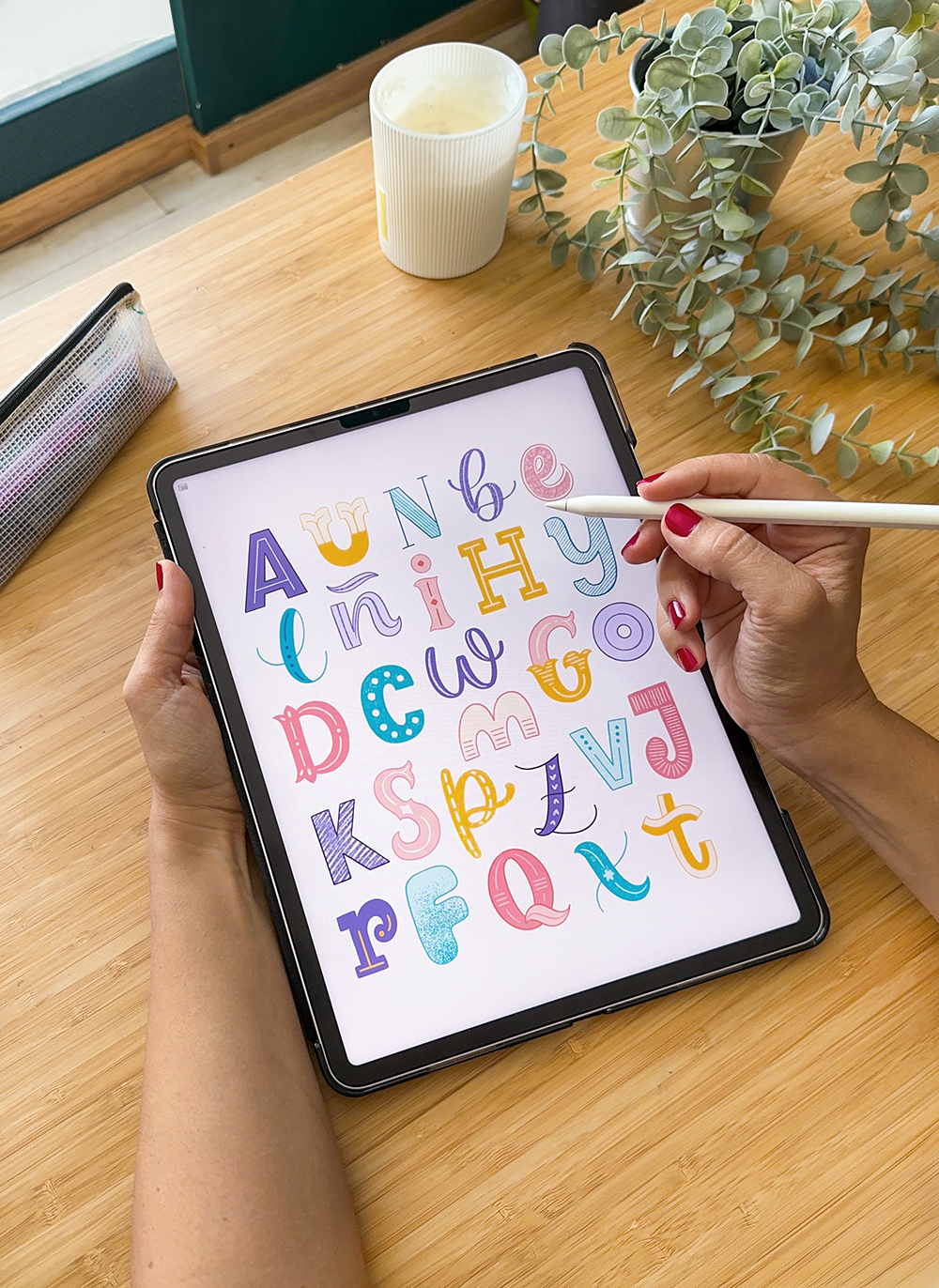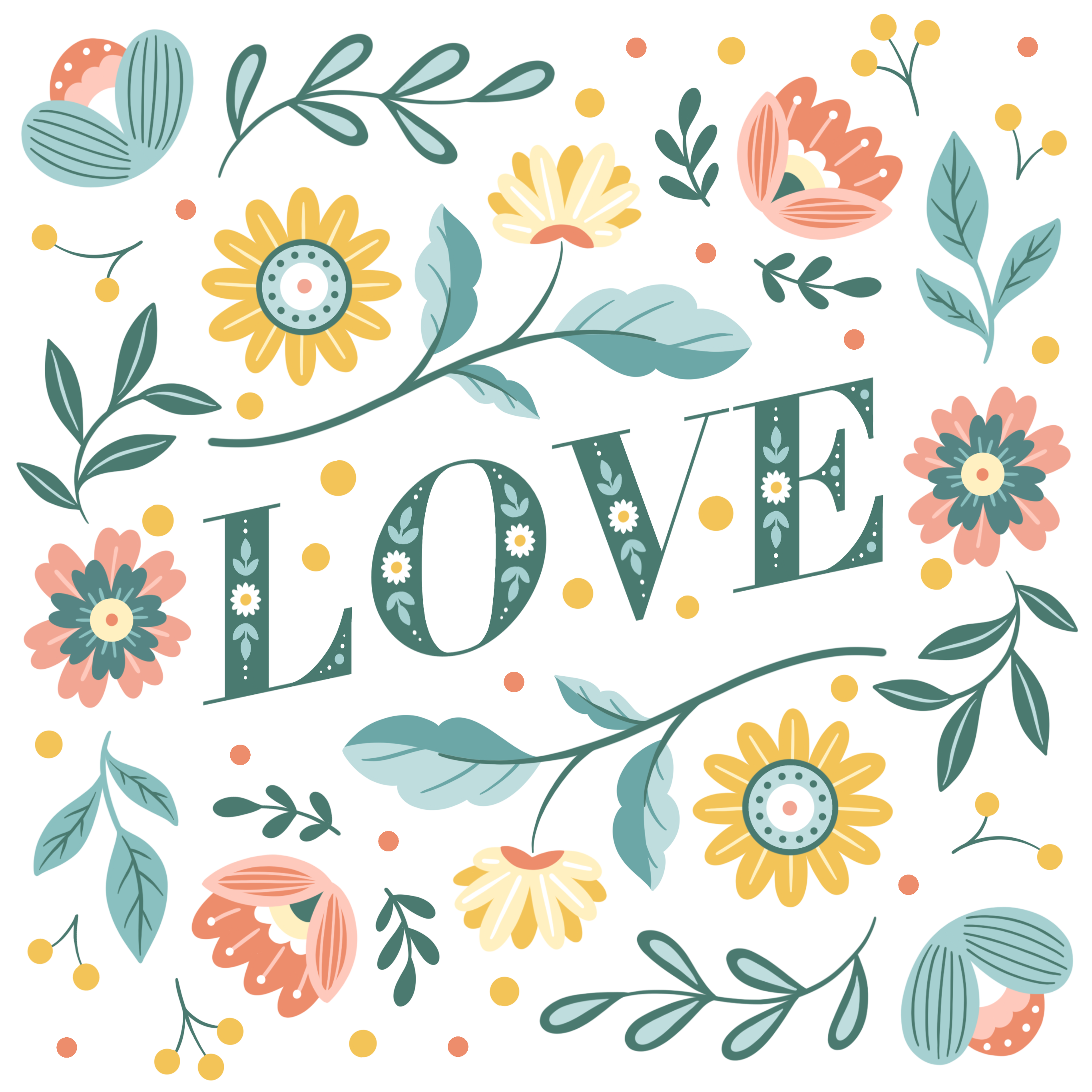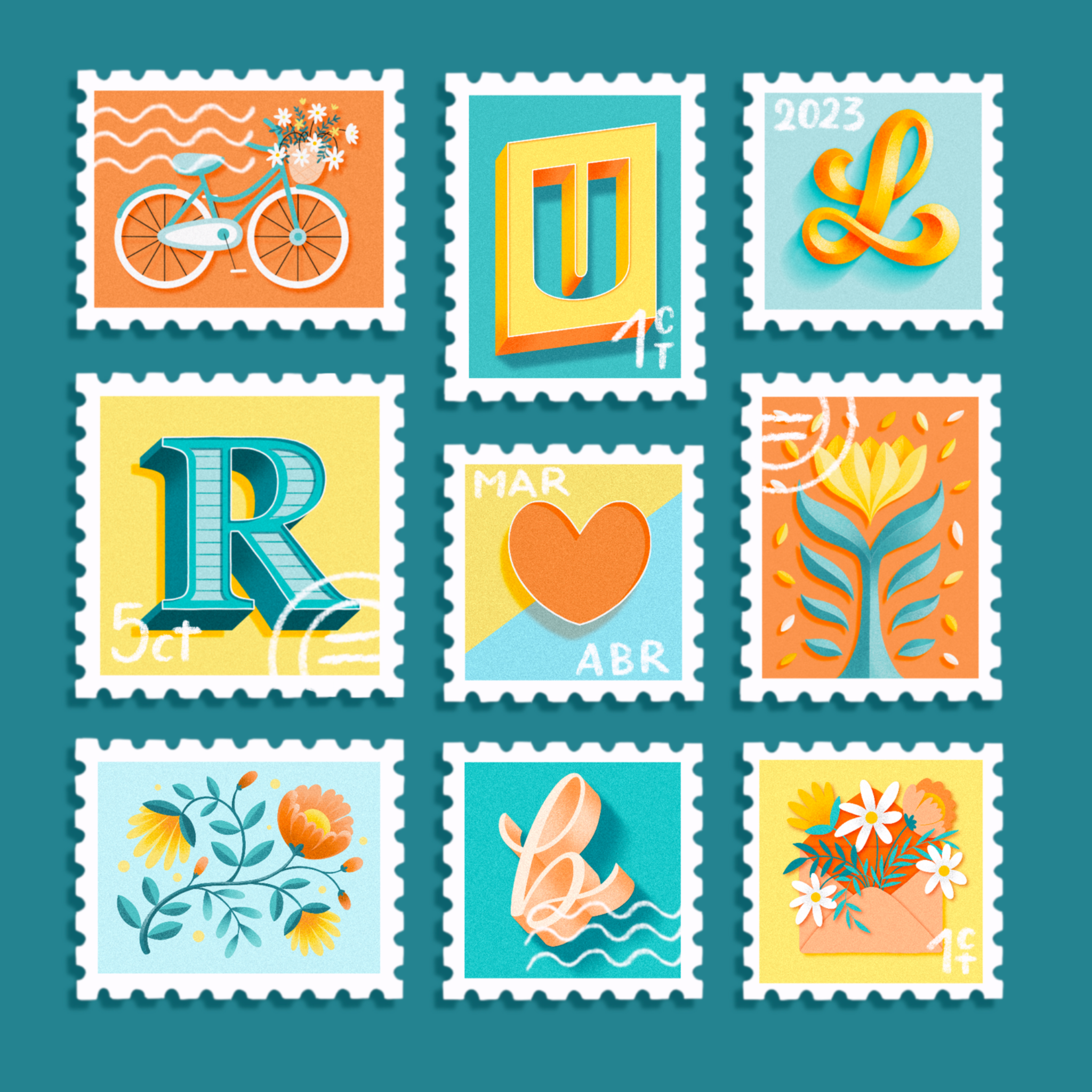
Crea con Procreate diferentes diseños que combinan lettering e ilustración, y que descubre todo lo que puedes hacer con ellos.
Aquí tienes los proyectos que aprenderás a hacer
en estas clases:
Dibuja letras con volumen en diferentes estilos
Serif, sans serif, script... cualquier estilo es válido para jugar con efectos 3D, ¡y Procreate lo hace todo mucho más fácil!
Acompáñalas con ilustraciones a juego
Crea ilustraciones de temática floral utilizando una misma paleta para crear armonía y sensación de conjunto.
Y organízalos en una colección de sellos única
Una misma ilustración digital puede servirte para muchos proyectos distintos, y aquí la presentamos como una colección de sellos única y divertida.
Crea un póster de tu ciudad favorita
Aprende a dibujar diferentes tipos de paisajes y combínalo con ilustraciones para crear una lámina preciosa homenaje a tu ciudad.
Realiza un diseño con temática folk
Las ilustraciones florales con temática folk, llenas de pequeños detalles, son perfectas para combinar con lettering y decorar cualquier objeto que se te ocurra.